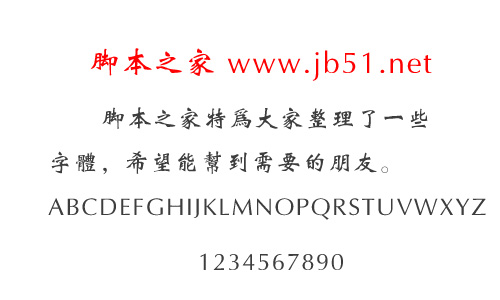
方正魏碑繁體字體是方正字體庫中的一種字體,魏碑體是北魏時(shí)期產(chǎn)生的一種介于漢晉隸書和唐楷之間的新書體,又稱為龍門體。方正魏碑的字形結(jié)構(gòu)跌宕起伏,筆意樸拙,不避鋒芒,規(guī)則中正。其風(fēng)格蒼勁堅(jiān)實(shí),適用于文化類的宣傳設(shè)計(jì),以及商業(yè)類品牌的廣告和產(chǎn)品包裝設(shè)計(jì)。喜歡的朋友們可以前來下載使用。